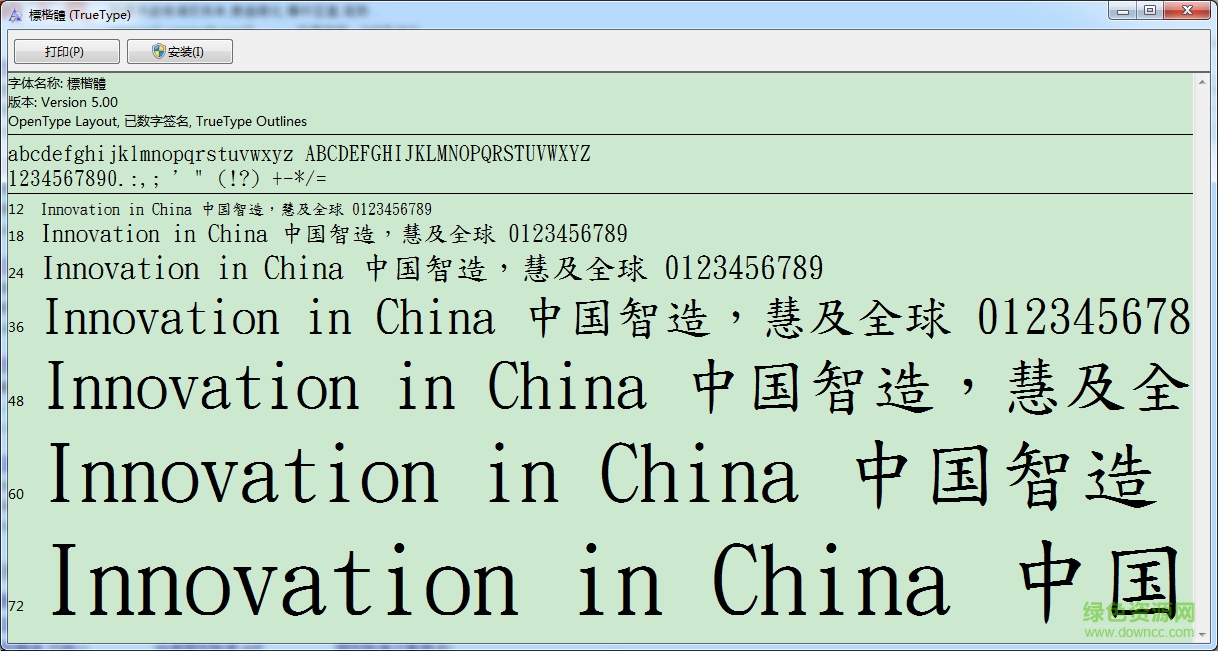
标楷体繁体字体
标楷体繁体是微软根据台湾教育部的国字标准字体标准打造的一款中文输入字体,形体方正,笔画平直,非常的美观,喜欢这款字体的朋友可以来绿色资源网下载使用!
标楷体繁体简介
标楷体是微软公司开发的TrueType中文字型。标楷体字形的整理,是以传统楷体为原型,并严格按照汉字的字源原则而制定的,其中区分了许多近世所混淆的字形构件,强化了汉字的科学性,便于学习使用。
标楷体繁体